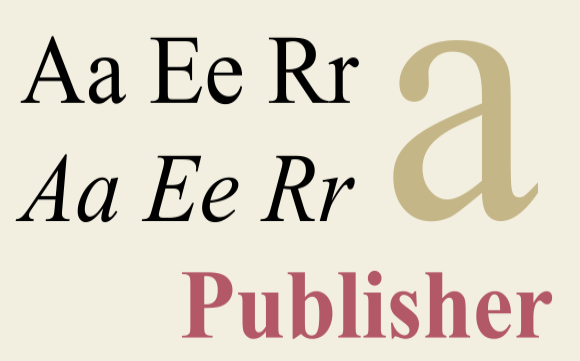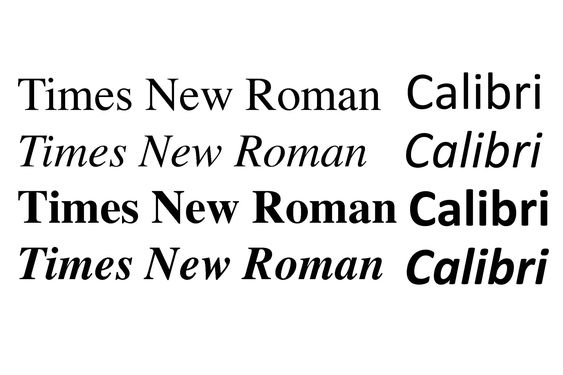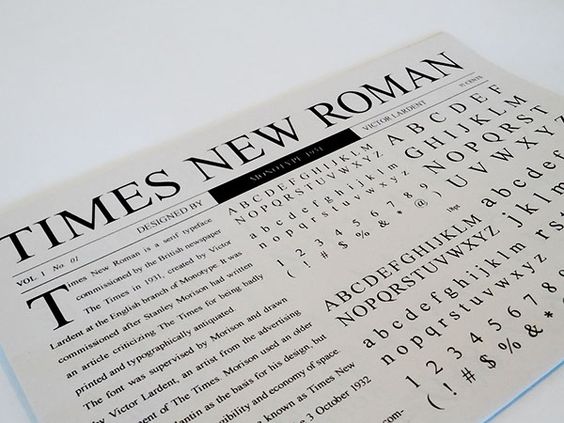
Font VN Time New Roman
Ngôn ngữ: Tiếng Việt, Tiếng Anh
Bộ Font: Font VN
Phân loại: Cổ điển
Kiểu chữ: Serif
Độ dày: Thin, Light, Regular, Medium, Bold, Black
Khi nói đến việc lựa chọn font chữ cho các văn bản tiếng Việt, VN Time New Roman là một trong những lựa chọn hàng đầu, mang lại sự hài hòa và dễ đọc. Font VN Time New Roman này thuộc bộ font chữ có chân không chỉ kế thừa sự trang nhã và chuyên nghiệp từ Time New Roman, mà còn được tối ưu hóa cho tiếng Việt với đầy đủ các ký tự có dấu, giúp việc soạn thảo và trình bày tài liệu trở nên dễ dàng và chuyên nghiệp hơn. Việc sử dụng đúng font chữ có thể ảnh hưởng trực tiếp đến trải nghiệm đọc và tính thẩm mỹ của văn bản, đặc biệt trong các tài liệu quan trọng như báo cáo, luận văn hay sách giáo khoa.